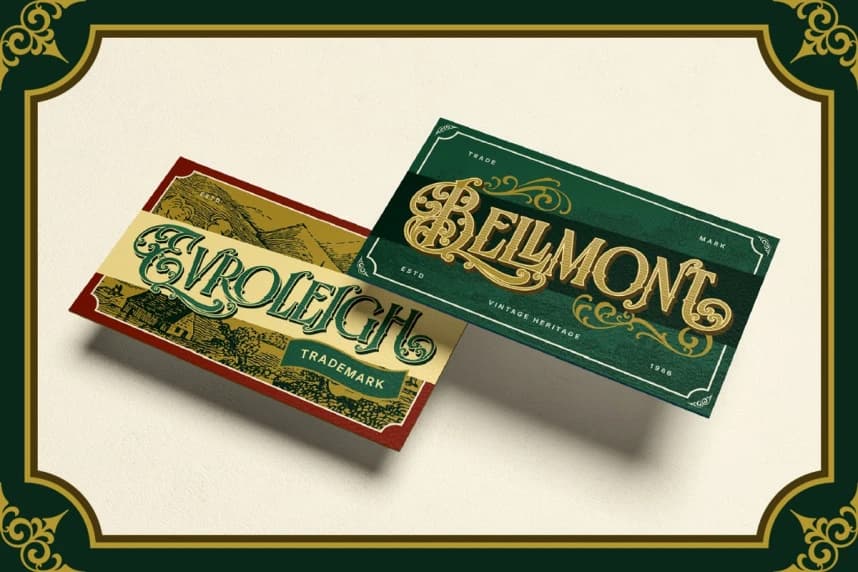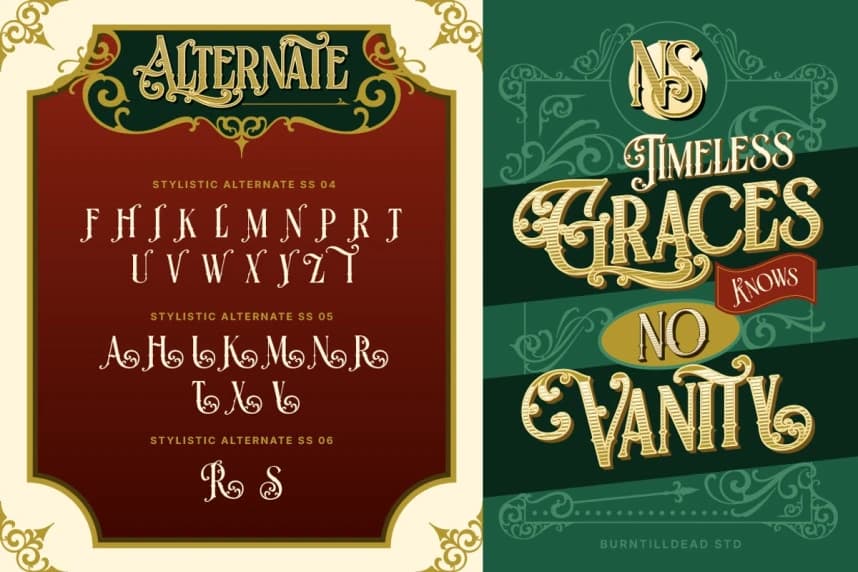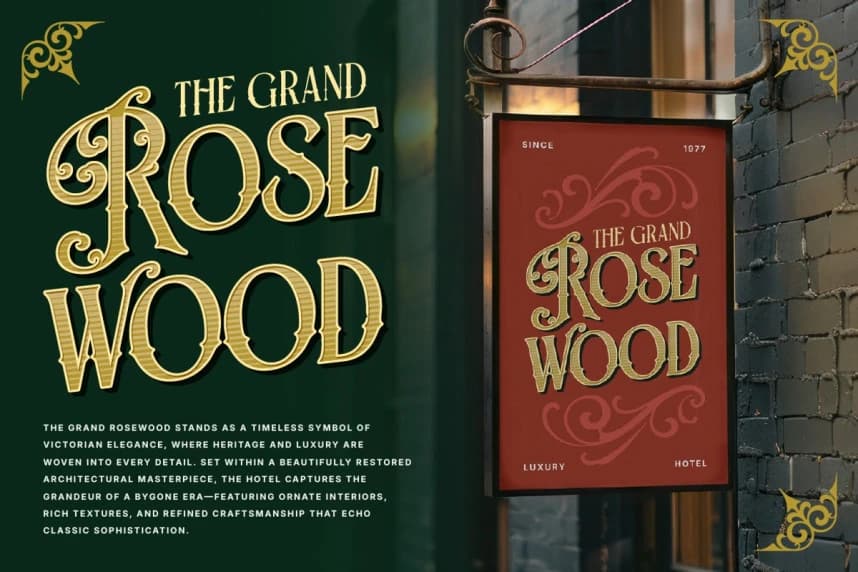
Blazter Yazı Tipi
Blazter Font, tasarımlarınıza zarafet, vintage cazibe ve cesur bir karakter kazandırmak üzere tasarlanmış çarpıcı bir süsleyici Viktorya dönemi yazı tipidir. 19. yüzyılın klasik tipografisinden ilham alan bu yazı tipi, karmaşık sarmalar, süsleyici detaylar ve özenle oluşturulmuş katmanlı bir sisteme
Blazter Font, tasarımlarınıza zarafet, vintage çekicilik ve cesur bir karakter kazandırmak için tasarlanmış göz alıcı bir dekoratif Victorian yazı tipidir. 19. yüzyılın klasik tipografisinden ilham alan bu yazı tipi, ayrıntılı kıvrımlar, süsleyici detaylar ve özenle tasarlanmış katmanlı bir sistem sunar.